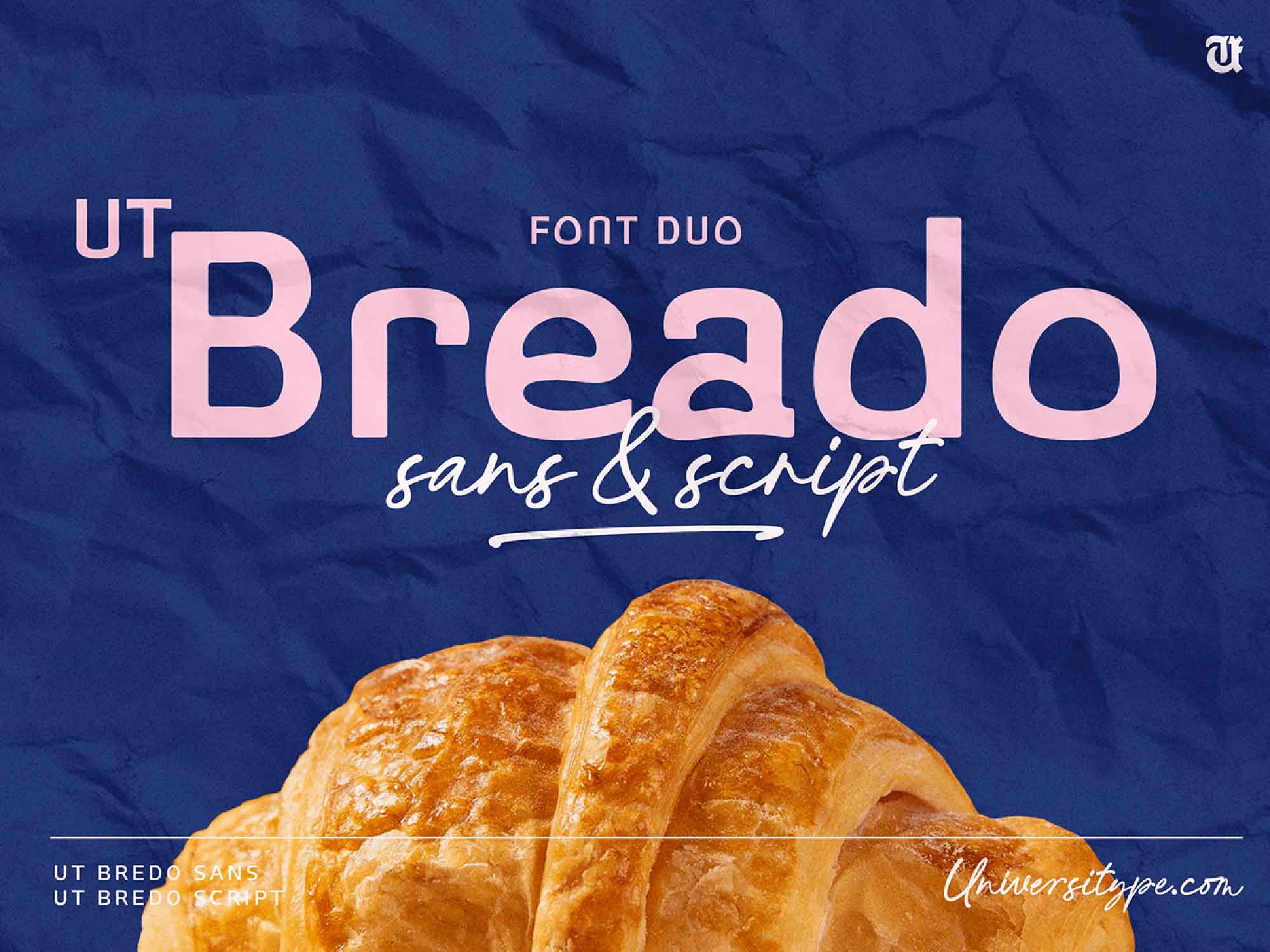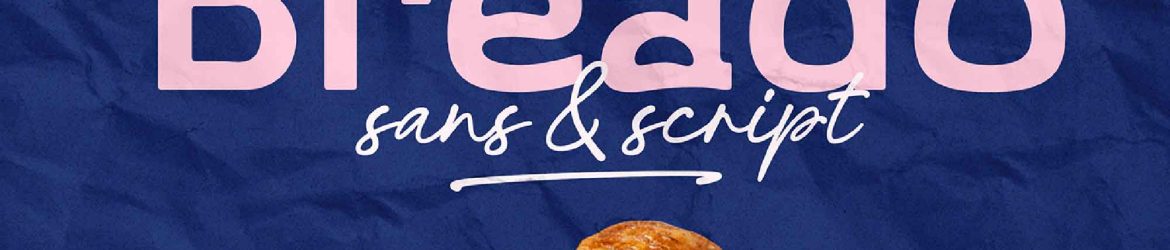
A UT Breado Font Duo é uma combinação única e atraente de caracteres sobrianos com formas de biscoitos, inspirada na essência da culinária e do processo de cozinhar. Este tipo de fonte único está disponível em três formatos e inclui dois estilos distintos, tornando-o especialmente legível em tamanhos diferentes. É perfeito tanto para o texto principal quanto para as seções de destaque. Oferecemos tanto versões premium quanto versões de avaliação gratuita para que você possa experimentar e usar o UT Breado Font Duo em suas projetos.